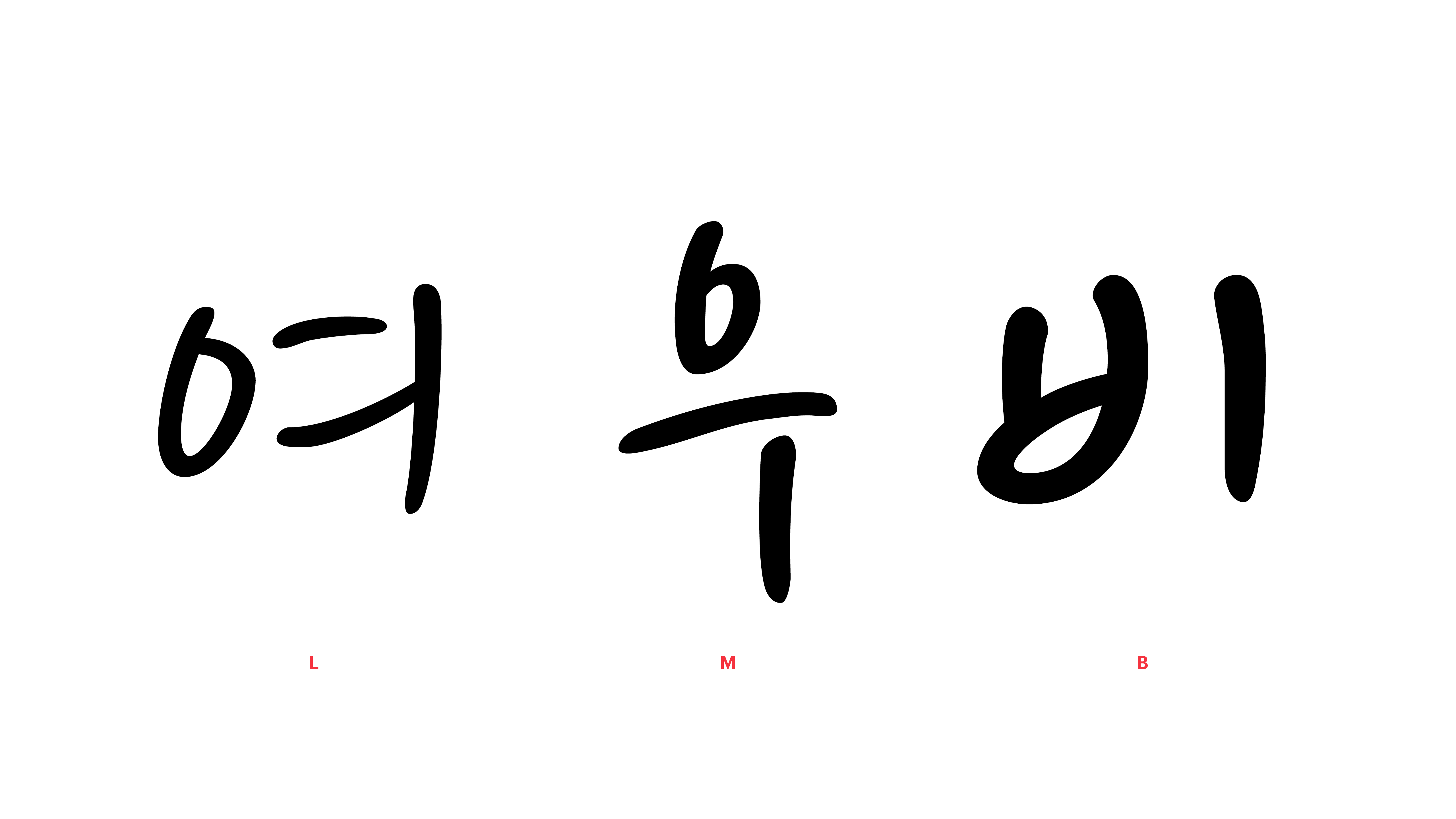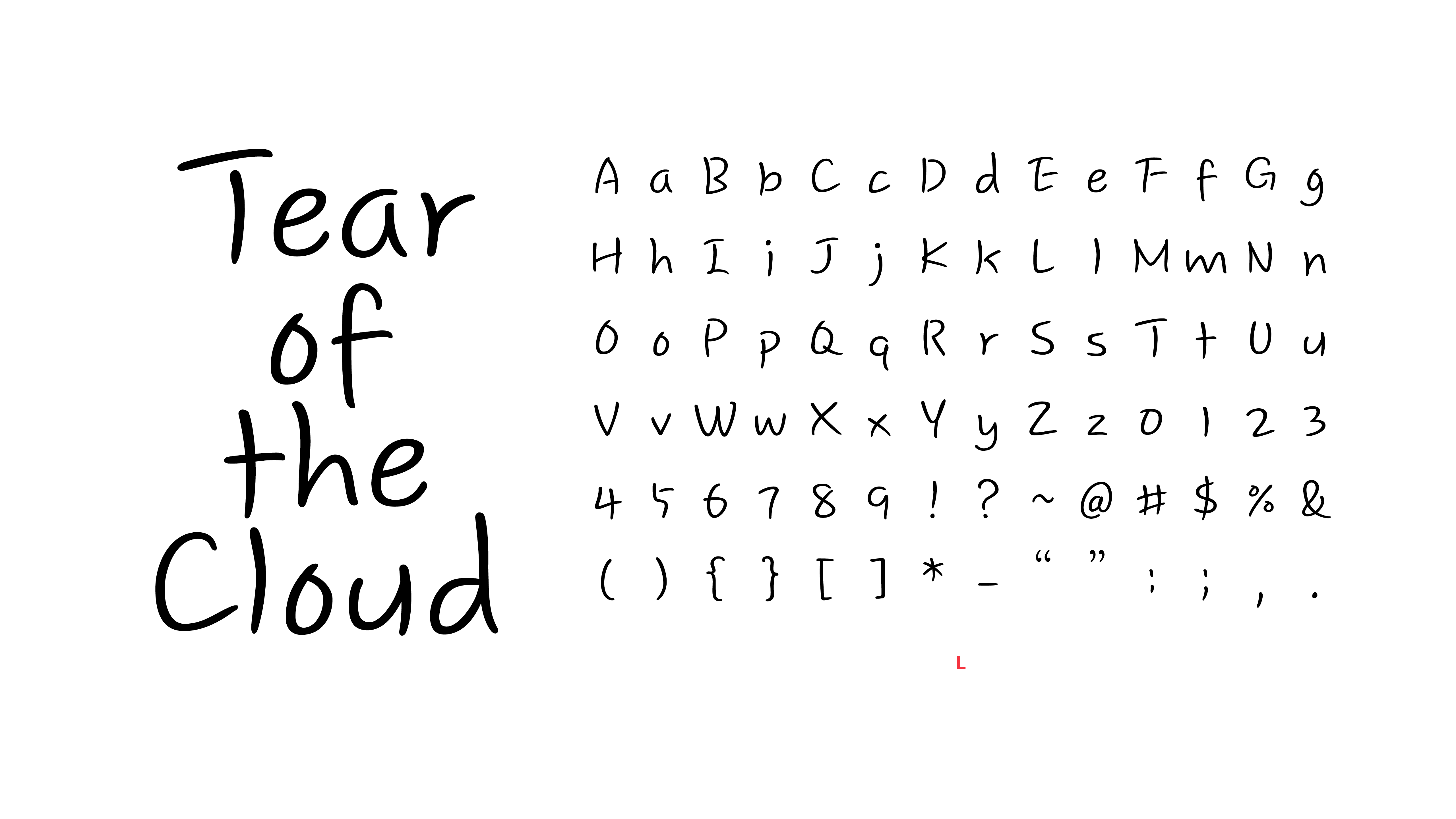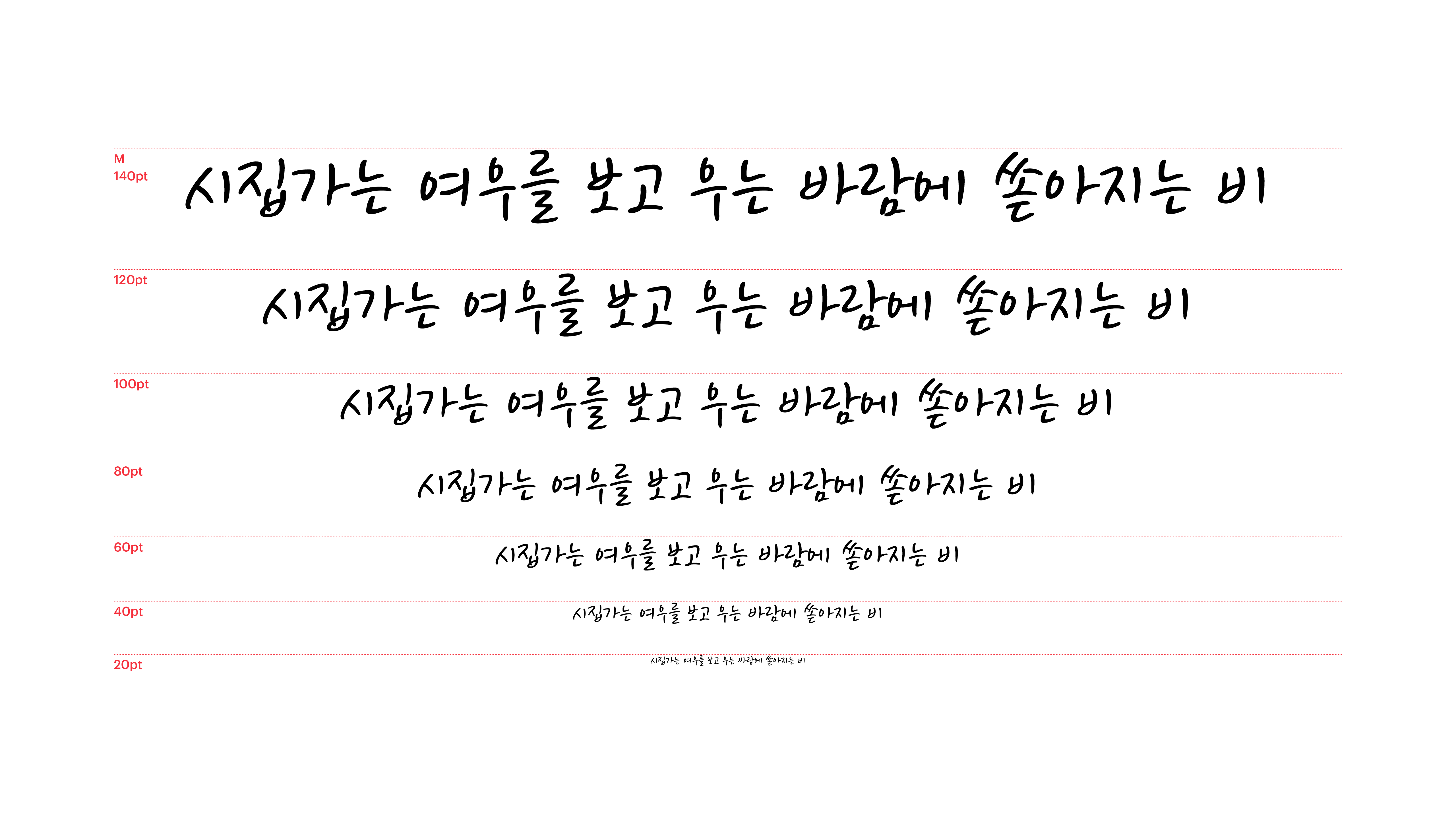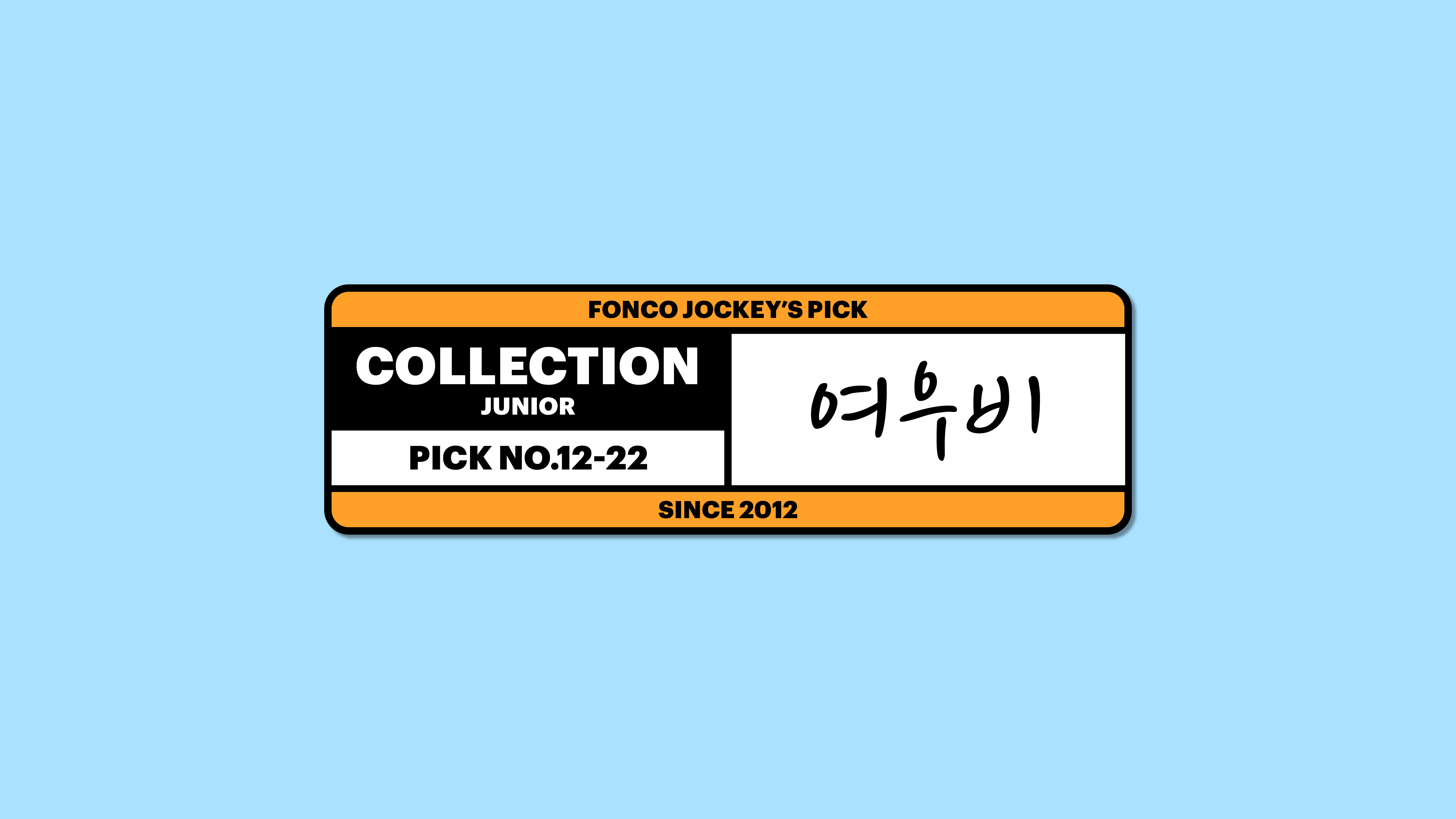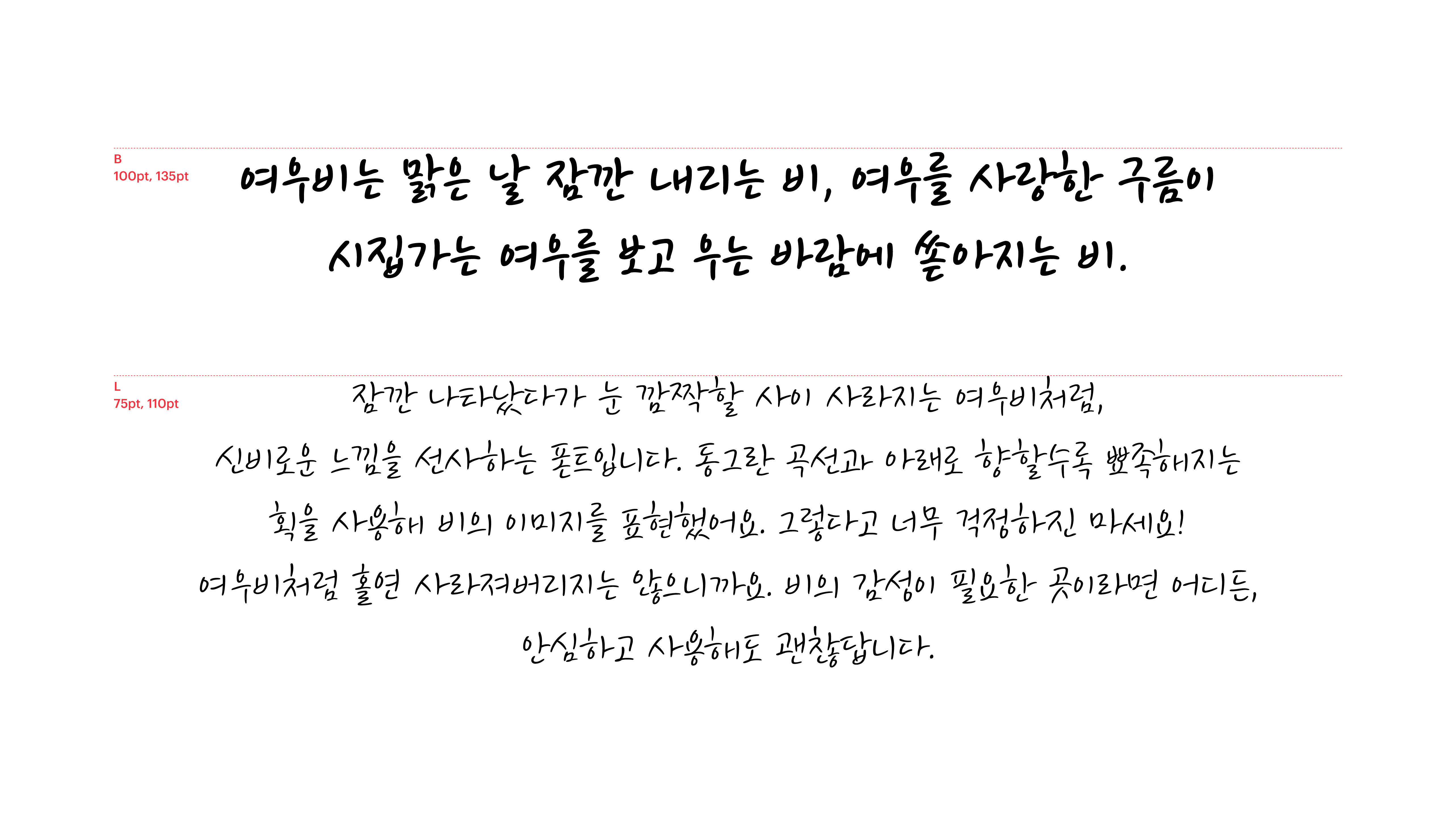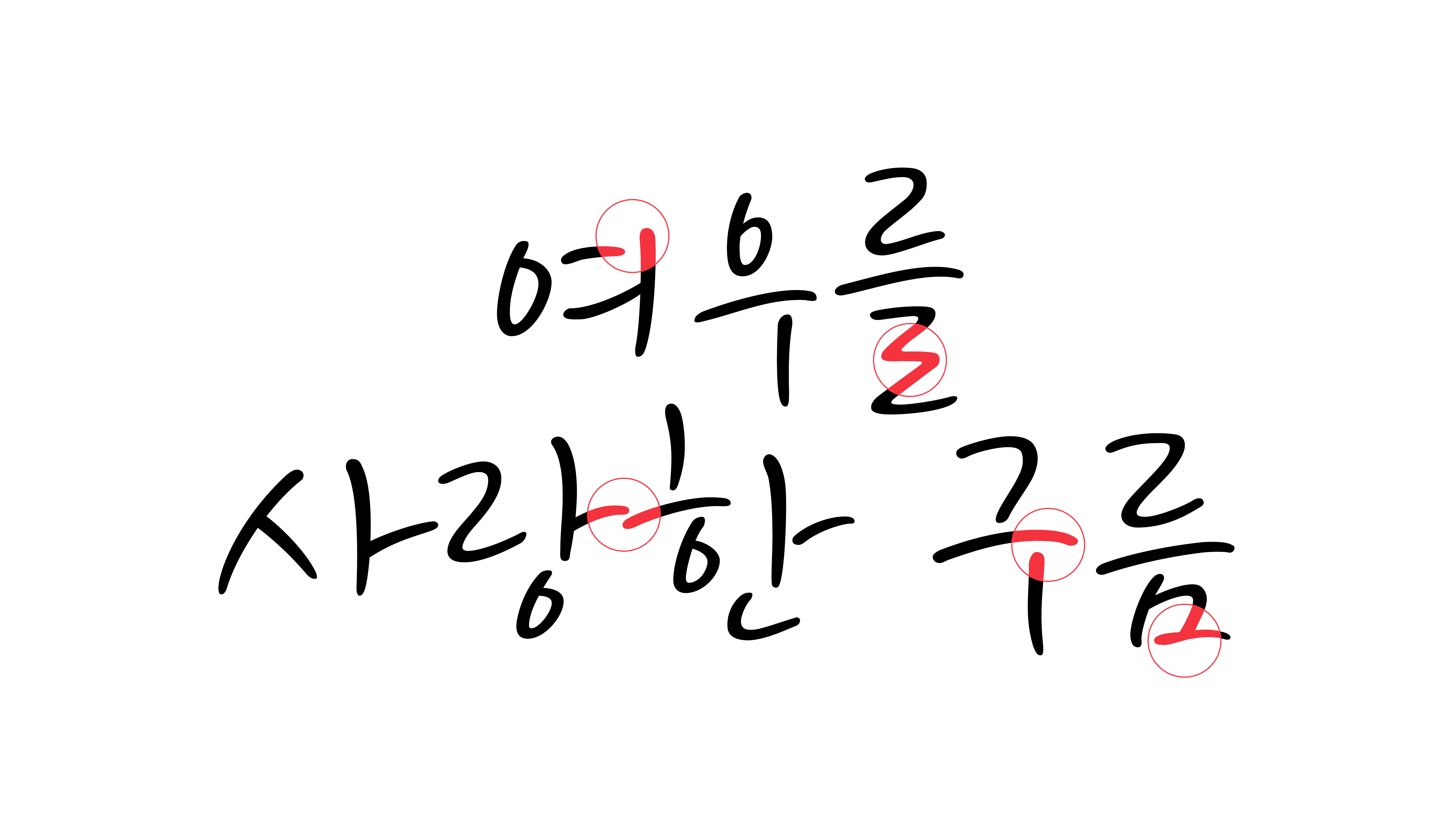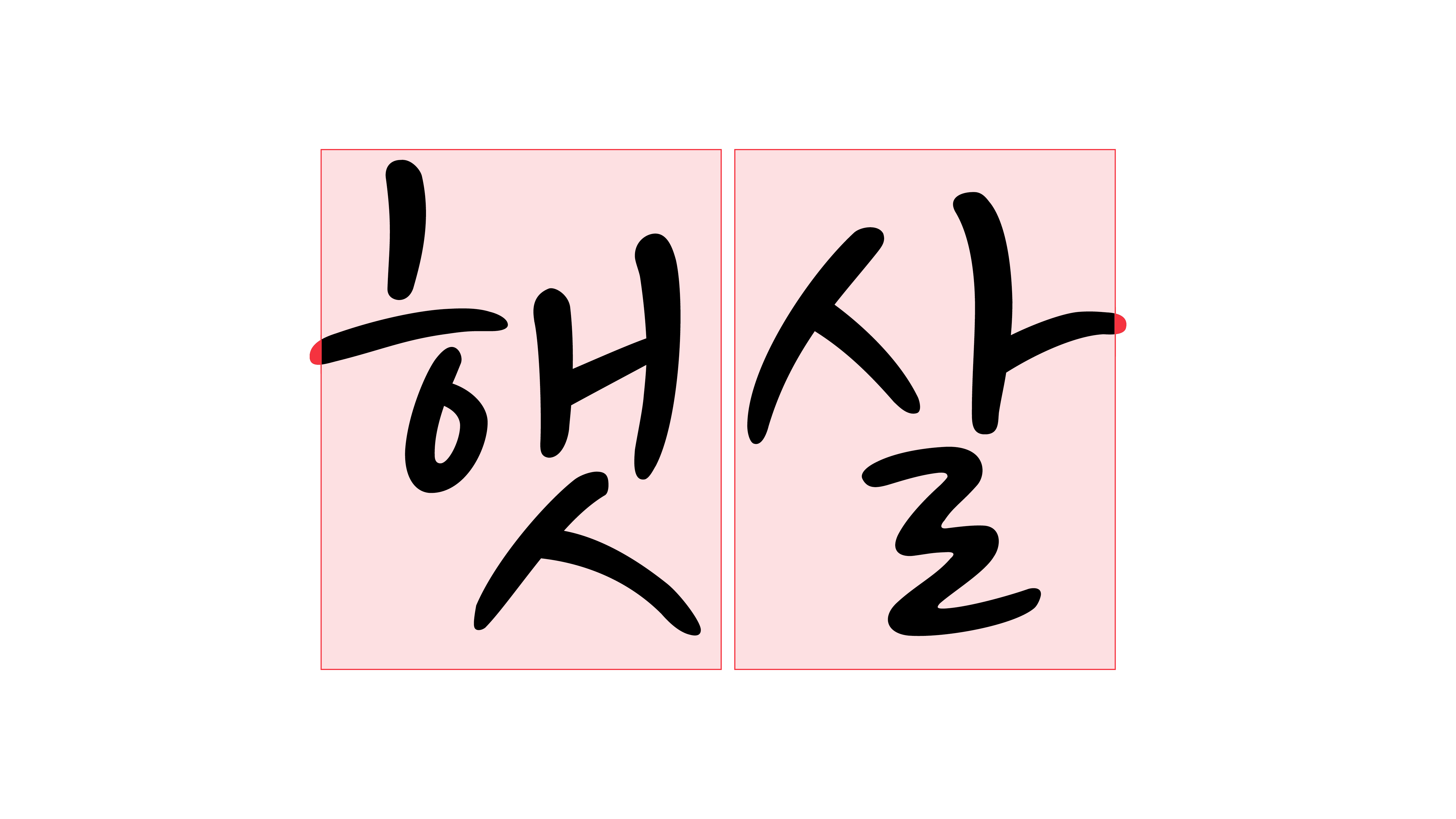
여우비
Yoon 여우비
잠깐 나타났다가 눈 깜짝할 사이 사라지는 여우비처럼, 신비로운 느낌을 선사하는 폰트입니다. 동그란 곡선과 아래로 향할수록 뾰족해지는 획을 사용해 비의 이미지를 표현했어요. 그렇다고 너무 걱정하진 마세요! 여우비처럼 홀연 사라져버리지는 않으니까요. 비의 감성이 필요한 곳이라면 어디든, 안심하고 사용해도 괜찮답니다.